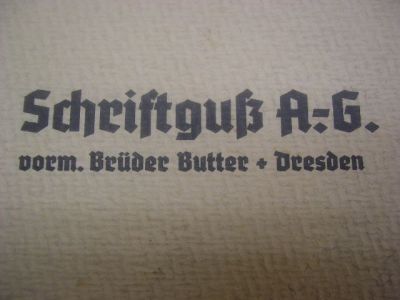
Kress Versalien
Also Leute, ob AG, KG oder VEB - alles stimmt, je nach Zeitpunkt. Aber Schriftguss Dresden hat sich vermutlich "nie" mit ß geschrieben!
So ein Fehler wird dann noch groß und breit in die Wikipedia übernommen und alle Beteiligten klopfen sich auf die Schulter. Davon wird es aber keinesfalls richtiger.
Bitte zeigt eure Geschäftsbriefe, Firmenstempel, Proben der Schriftguss Dresden mit ß. Ich kenne sie nur in der ss-Schreibweise.
ja, dass mit den quellen sehe ich auch so.
auf deren webseite steht leider auch nichts.
die sektor ist ja die ehemalige schrift der ddr-geldscheine
und die gretel ist aus einem kreuzstich musterbuch
auch da gibts leider keine quellenangaben.
ich schätze mal die vitus, emily und die diavolo sind auch
nicht zu 100 % aus eigener hand.
ih habe gerade nochmal bei meinem einzige schriftguss-
schriftmuster geschaut, minister antiqua, dort wurde
auch schriftguss mit ss geschrieben.
Die NE und PO (Negativ/Positiv) von Schriftguss hatte ich aus Spaß mal als Fonts umgesetzt, einfach um damit diese Typen "bauen" zu können. Aber sowas zu releasen war mir doch zu popelig. Auch Intermezzo basiert auf solchen Gundformen. Damals war das sicherlich auch eher ein Experiment. Ich kenne nur die Anwendugen aus dem Musterbuch. http://www.flickr.com/photos/astype/225 ... otostream/
Pixelgrafik gabs auch schon.
Okay meine besten, kann dann jemand mit besserem Quellenzugang bitte dann richtig stellen? Ich hatte auch gar nicht vor mir für das ändern dreier Zeichen auf die Schultern zu klopfen. Im übrigen finde ich, es gilt noch immer das was ich Georg oben schrieb: nicht meckern, ändern! Ich hatte im Rahmen meiner Möglichkeiten versucht zu recherchieren, beim Klingspor-Museum z.B., immerhin eine nach wissenschaftlichen Kriterien geführten Sammlung, schreiben sie auch »Schriftguß AG«. Ihr scheint aber Recht zu haben, auch Ralfs Flickr-Muster der Drescher Versalien deutet darauf hin. Bei Flickr hab ich zugegebenermaßen nicht vorher nicht geguckt, weil die mir die Bilder neuerdings nur noch in der Flash-Diaschau zweigen, was mir auf die Nervern fällt. Vielleicht wollt Ihr ja zur Überprüfung noch dieses Muster aufkaufen, ist ja im Vergleich zu Euren sonstigen Ebay-Orgien geschenkt. :wink: Und wo ich schon bei Kauftipps bin: Stempels Avant-Garde-Werbung.
Bitte zeigt eure Geschäftsbriefe, Firmenstempel, Proben der Schriftguss Dresden mit ß. Ich kenne sie nur in der ss-Schreibweise.
Hallo Andreas,
wir beiden hatten genau dieses Thema schon einmal am: 17. Jun. 2006 12:40 kurz diskutiert:
Dieses Photo (kompletten Scan kann ich erst Montag nachliefern) stammt von einer Schriftmusterbroschüre der Schaefer-Versalien (1927). Die Gestaltung und der Druck der Broschüre dürfte aus der Mitte der 1930er Jahre stammen.
Ok, dies ist Schriftguss mit ß. Allerdings hier in gebrochenen Lettern. Bisher habe ich Schriftguss immer nur in Antiqua mit ss gesehen. Alle meine Proben (unterschiedliche Publikationen) aus den 30er Jahren, sind in Antiqua und immer mit ss, auch im Minuskelsatz. Die Eigenwerbung in Fremdpublikationen, Klimsch Jahrbücher usw., kenne ich auch nur mit ss.
Auf ZVAB gibt es einige Rechnungen mit Bild von Schriftguss - alle mit ss.
Für mich ist das so etwas wie ein Running Gag der Schritguss AG. Nach dem Motto: „Es gibt zwar den Schriftguß aber nur die Schriftguss AG“ oder "Wir sind eben anders als die anderen." – „Och, schau mal, da hat uns wieder einer falsch geschrieben."
Im Deutschen Buchdrucker Kalender für 1929, zum Beispiel, wird im redaktionellen Teil die Schriftguss im ß gesetzt, die Eigenwerbung von Schriftguss jedoch wieder mit ss. Tja, und so werden wohl die diversen Schreibweisen zustande kommen.
Das Beispiel von Georg halte ich für ein Kuriosum, evtl. weil der Name in einer gebrochenen Letter gesetzt werden mußte. Schaut mal in Zeitschriften oder Jahrbüchern nach. Es wäre sehr verwunderlich wenn dort auch nur einige Eigenanzeigen in der ß-Schreibweise auftreten sollten.
Ok, dies ist Schriftguss mit ß. Allerdings hier in gebrochenen Lettern. Bisher habe ich Schriftguss immer nur in Antiqua mit ss gesehen. Alle meine Proben (unterschiedliche Publikationen) aus den 30er Jahren, sind in Antiqua und immer mit ss, auch im Minuskelsatz. Die Eigenwerbung in Fremdpublikationen, Klimsch Jahrbücher usw., kenne ich auch nur mit ss.
Auf ZVAB gibt es einige Rechnungen mit Bild von Schriftguss - alle mit ss.
Ich schaue aber gern nach, was ich bei mir finde. Einen echten Aussagewert dürften dabei aber immer nur Originalbelege der Schriftguß selbst sein. Mich interessiert das Thema sehr. Man möchte doch in der Schriftensammlung des eigenen Netzauftrittes nichts Falsches kommunizieren.
Die Schriften der Schriftguß gehören für mich schon lange zu den schönsten, die es vor dem Krieg gegeben hat.